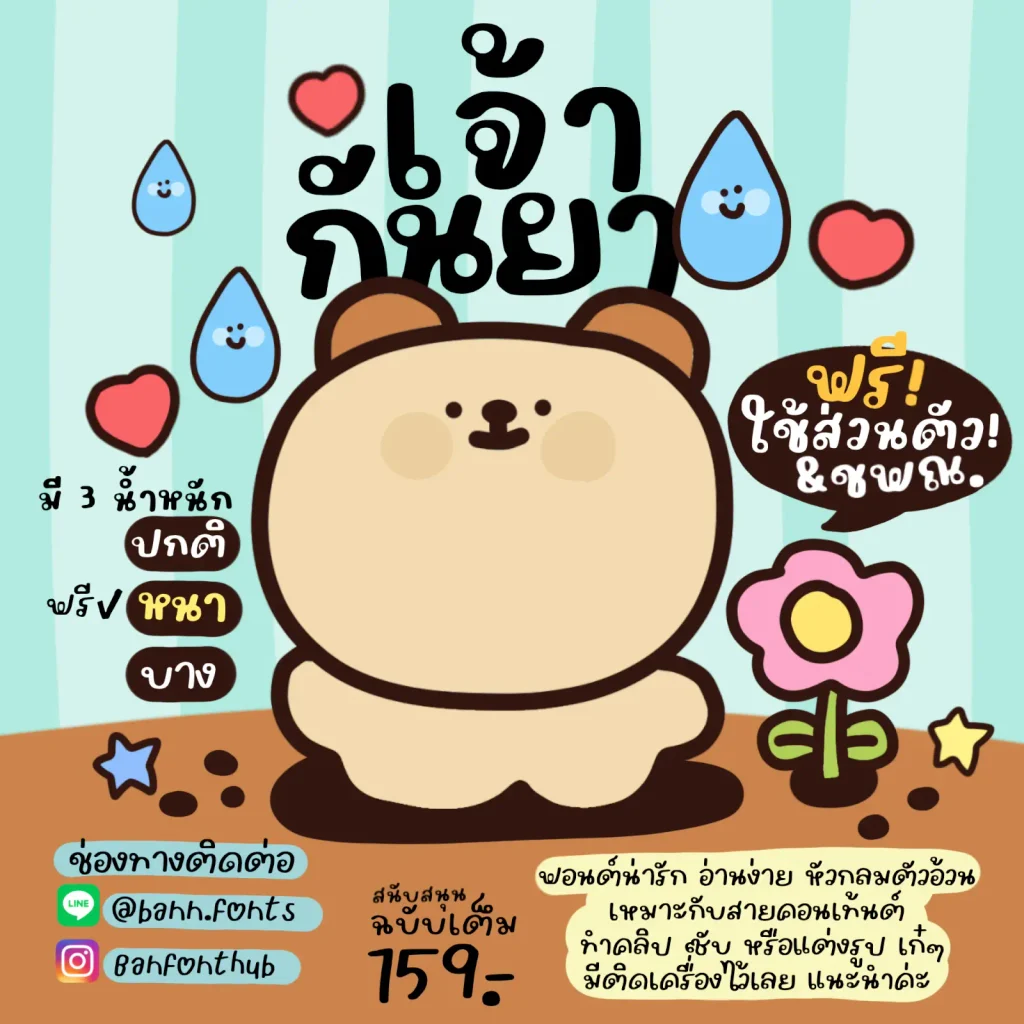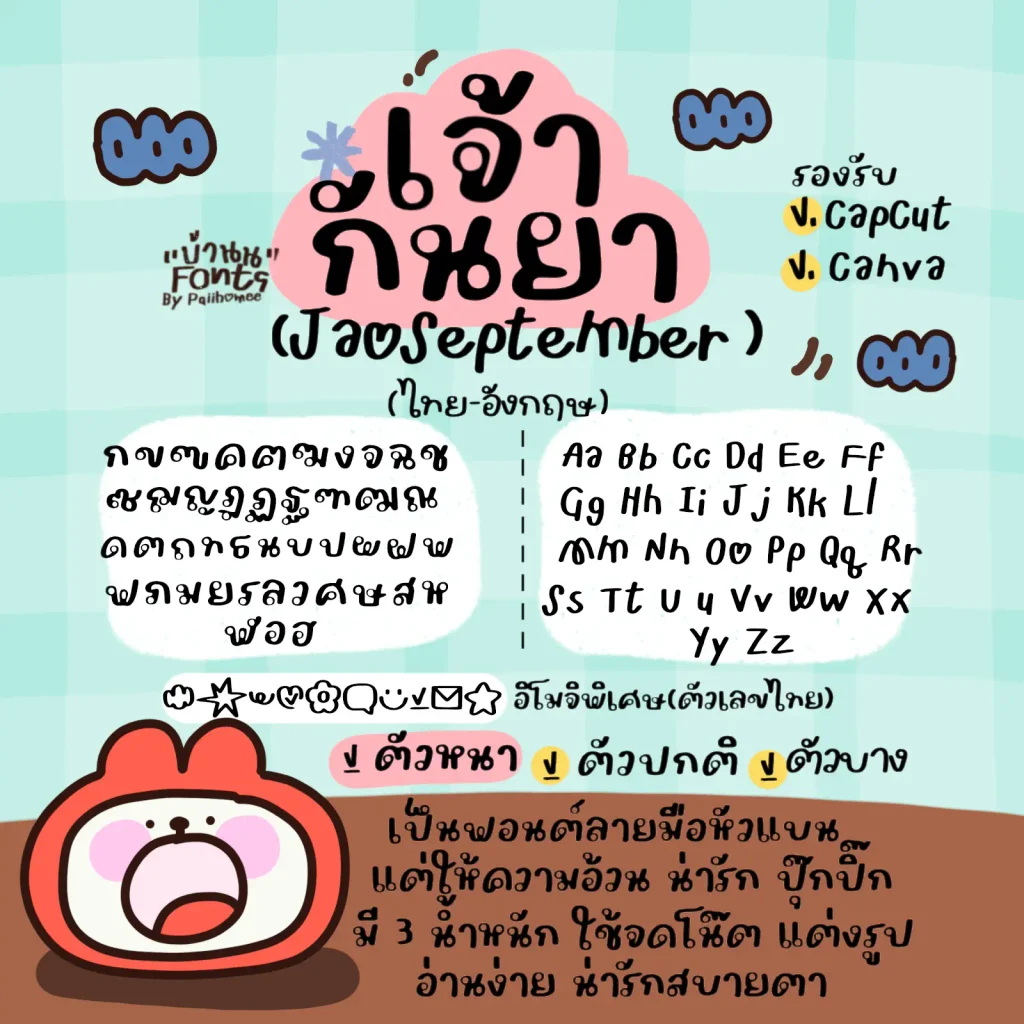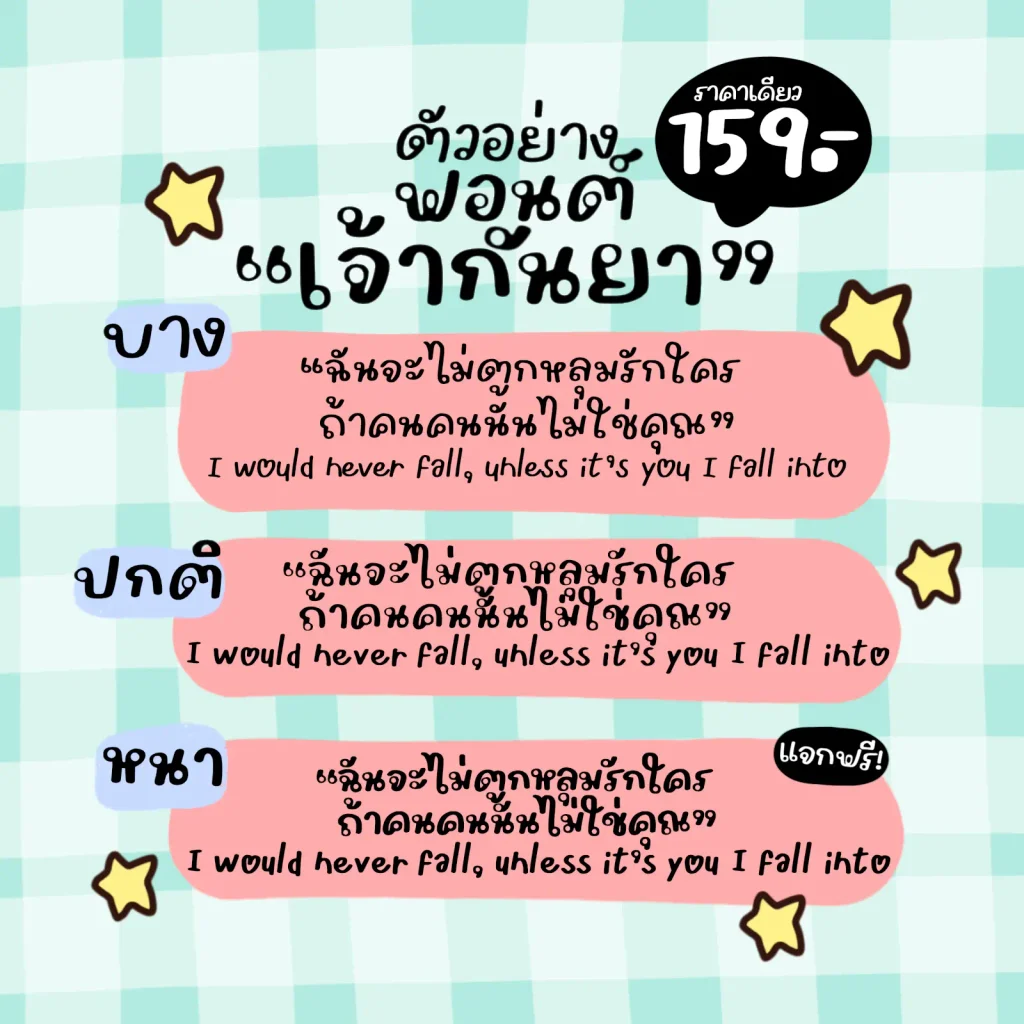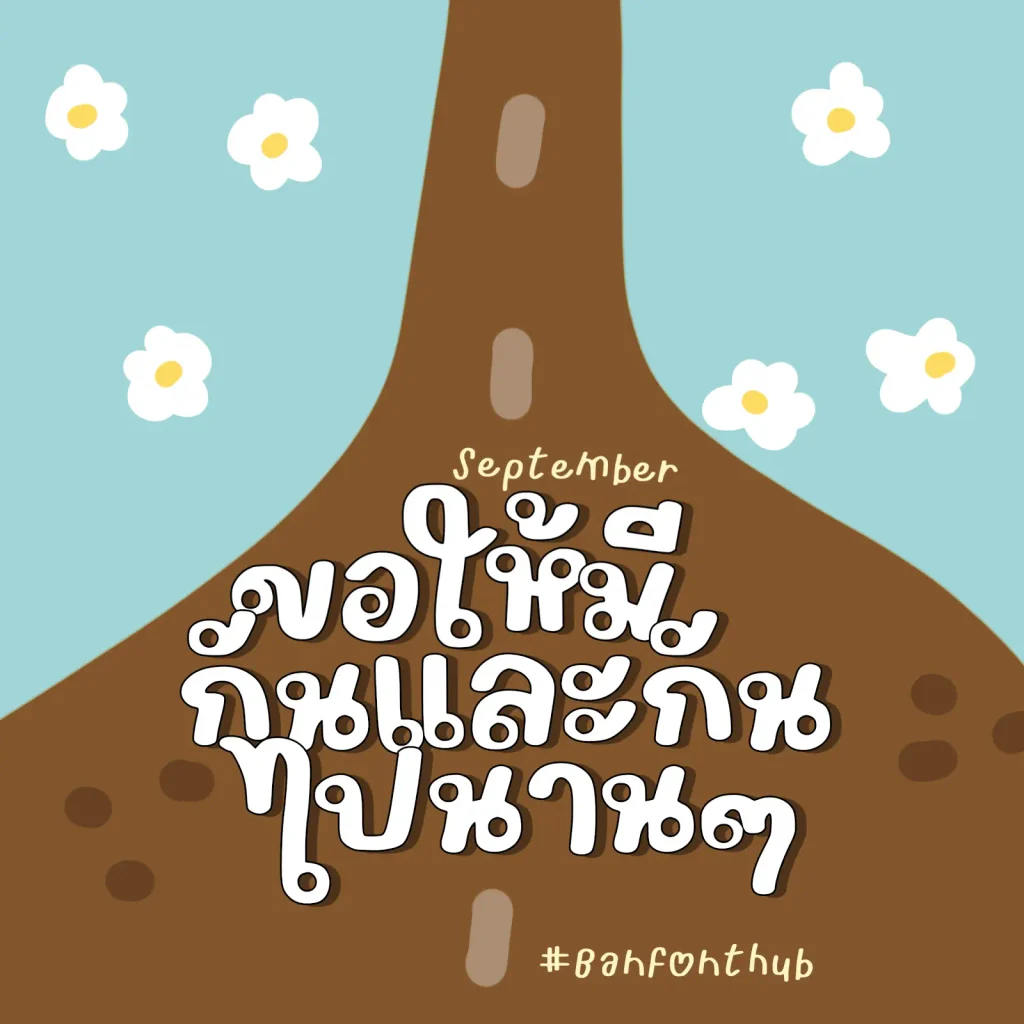
ฟอนต์เจ้ากันยายน ☔️ – 📌แจกฟรี ! ฉบับรุ่นตัวหนาเท่านั้น! ใช้งานฟรี! ทั้งแบบส่วนตัวและเชิงพาณิชย์
แจกให้ใช้งานฟรี! สำหรับคนที่ชอบฟอนต์ลายมือ น่ารักๆ หัวโตๆ อ่านง่าย มีความน่ารัก x10!
✍🏻แนะนำว่า นำไปใช้งานกับการเขียนปกคลิป ปกรูป สรุปงาน จดโน้ต จดบันทึก หรือจะนำไปทำคลิป แต่งรูป ก็เริ่ดสุดๆ แนะนำเลย
เจ้ากันยา (JaoSeptember)